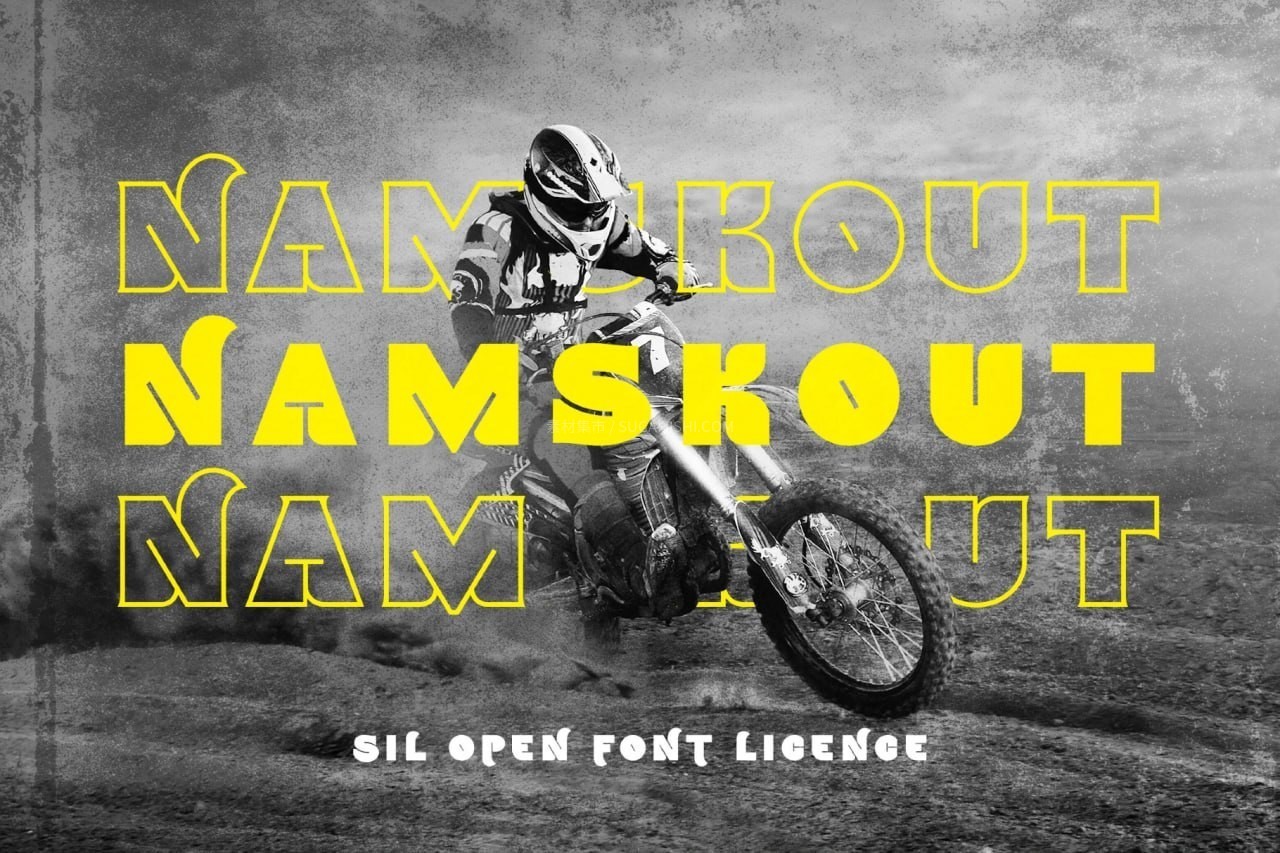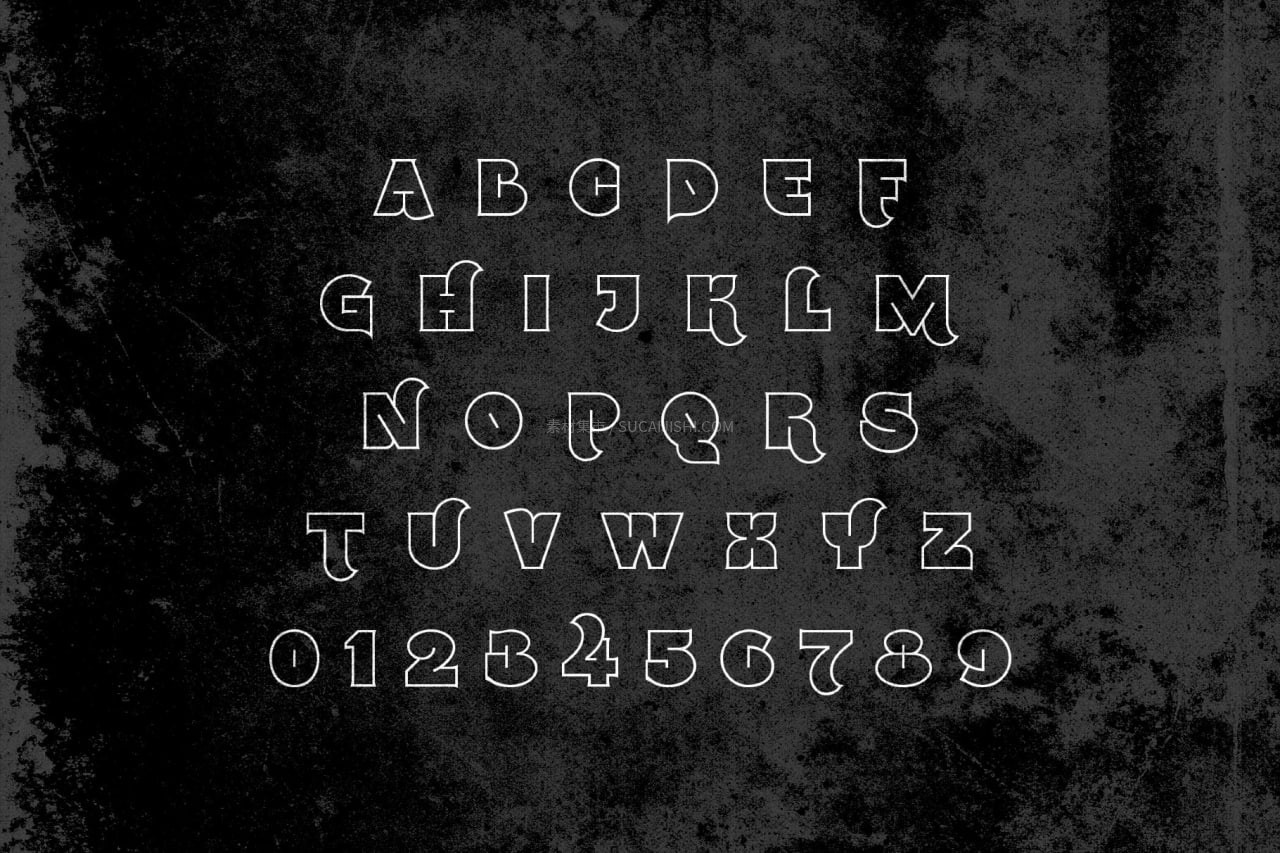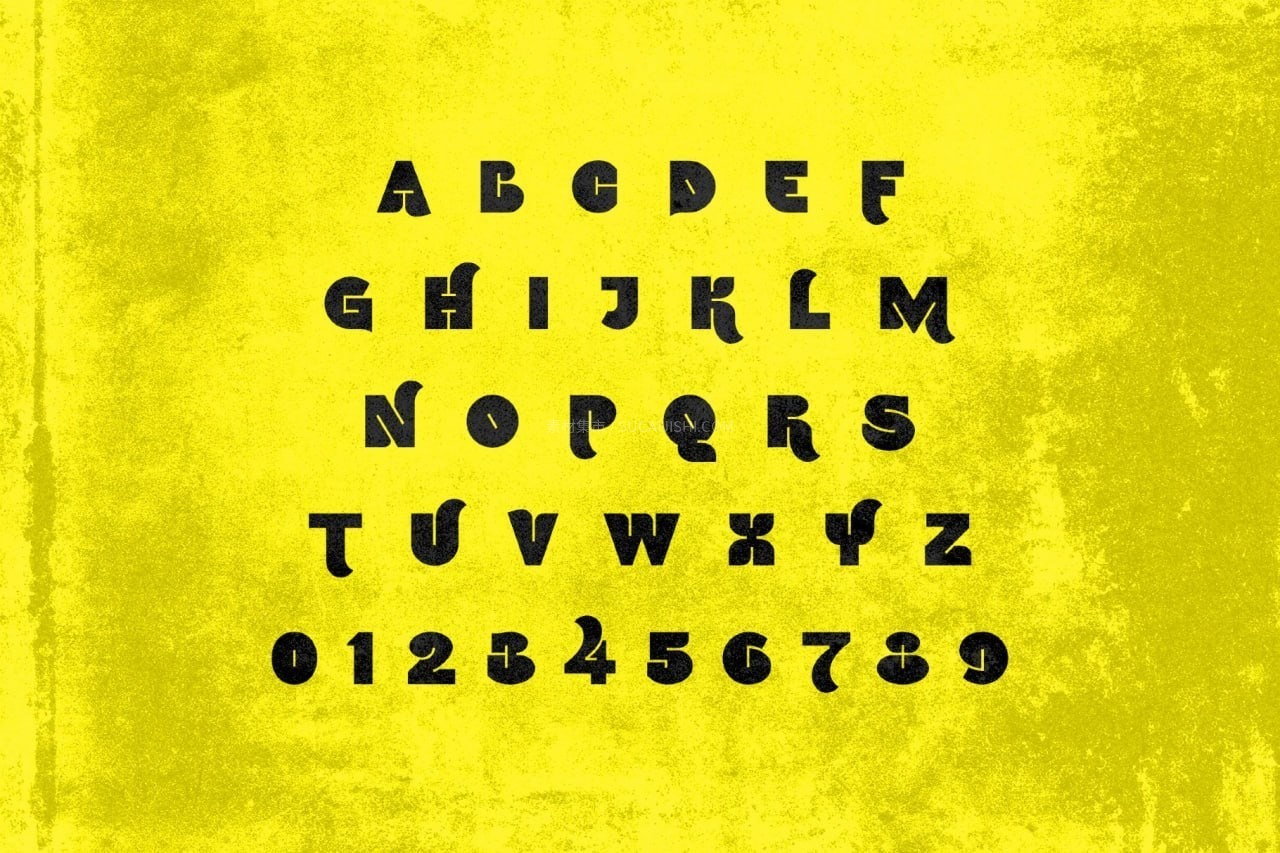
Namskout亲和力粗体英文字体,免费可商用
这是一套由 Namskout、Namskin 和 Namskoutin 共同构成的粗体字体家族。字体外观圆润饱满、亲切可爱,涵盖了轮廓体、实心体、混合体三种互补风格。用户可以将不同风格进行层次叠加或混合使用,轻松创造出极具层次感和趣味性的视觉特效。本套字体附带 OFL 开源协议,支持免费商业用途,是设计师工具箱中不可多得的创意利器。